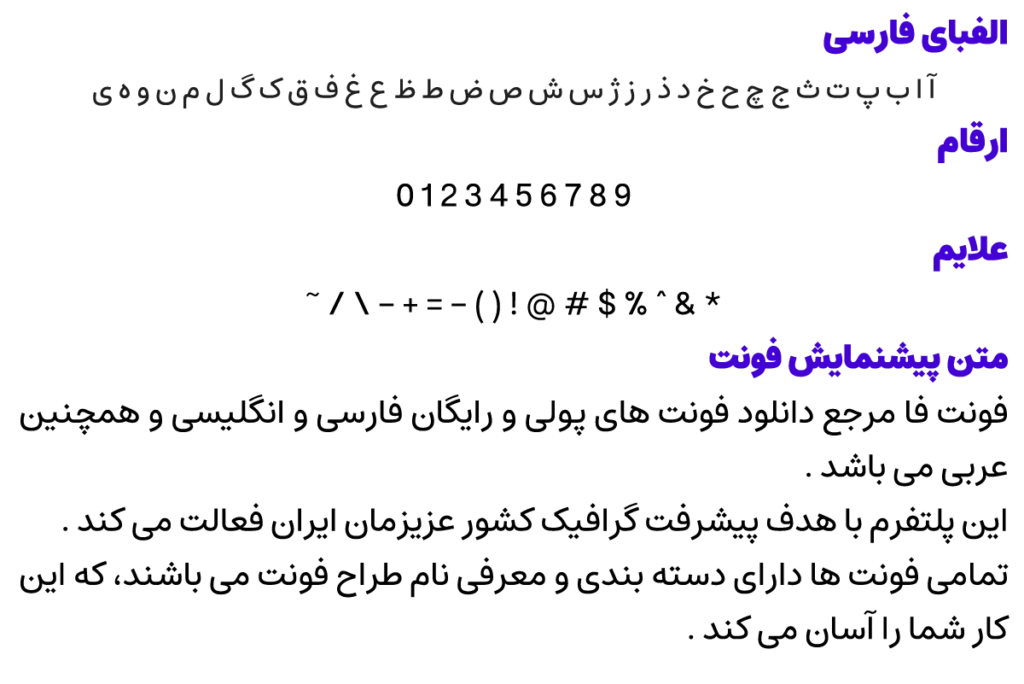
فونت فارسی استعداد – Estedad
طراح فونت: امین عابدی نوع فونت: فونت طراحی وب و فونت عنوان و فونت متن
توضیحات و معرفی فونت استعداد
فونت فارسی استعداد ( Estedad ) از مجموعه فونت های آزاد می باشد، همچنان نوع فونت طراحی وب و عنوان و متن می باشد.
فونت شگفت انگیز و زیبای فوق توسط امین عابدی در سال 1396 طراحی و ساخته شده است.
همچنین فونت استعداد مَد از روی تایپفیس استعداد بازطراحی و نسخه ضخیمتر می باشد.
همچنان فونت استعداد در 9 وزن سنگین و پر رنگ و نیمه پر رنگ و فوق العاده پررنگ و سبک و متوسط و معمولی و نازک و فوق سبک است.
نمونه عکس زیر نوشته شده با همین تایپ فیس زیبا